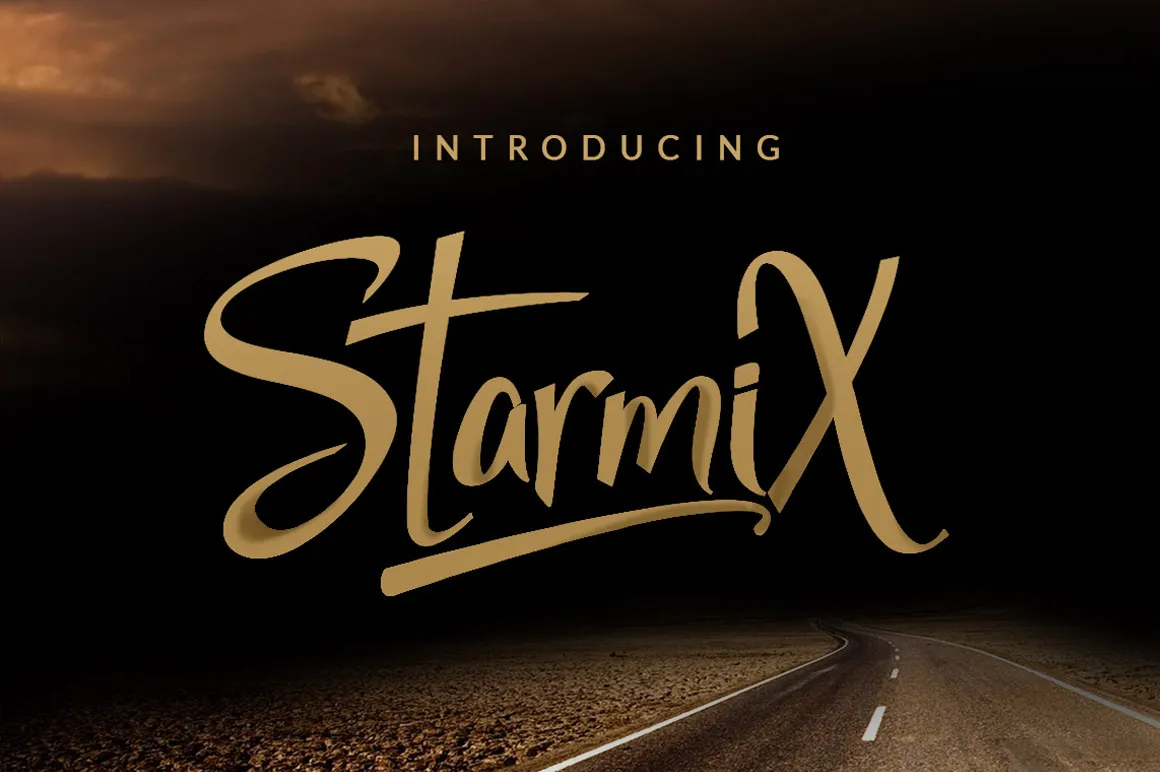
StarmiX Script Font
Aqui está uma versão em português do Brasil para a descrição solicitada: Explore novas fronteiras do design com StarmiX Script Font, uma fonte script inovadora de 178-MC. Introduzida pela equipe talentosa de Khurasan, esta fonte é um verdadeiro tratamento fresco e único no seu gênero. StarmiX traz multilinguismo em uma mistura de caracteres e swashes personalizadas feitas à mão. Esta fonte incorpora elementos únicos que vão desde novas formas de letras até adição de detalhes artísticos para criar um efeito chamativo e único. Seja você designer gráfico ou criador digital, StarmiX Script é uma escolha inteligente para qualquer projeto que valoriza personalização e originalidade. Em termos de uso, StarmiX Script Font oferece flexibilidade, permitindo a criação de layouts distintos e incrivelmente detalhados. Este design diferenciado não apenas vai capturar o seu público objetivo, mas também irá destacar seu trabalho em qualquer plataforma digital ou impressa onde a fonte for aplicada. Junte-se a nós neste novo caminho estelar da design do texto, e experimente StarmiX Script Font. Seja inspirador, inovador e único na maneira como você expressa seus projetos de design com essa novidade em alta tecnologia!